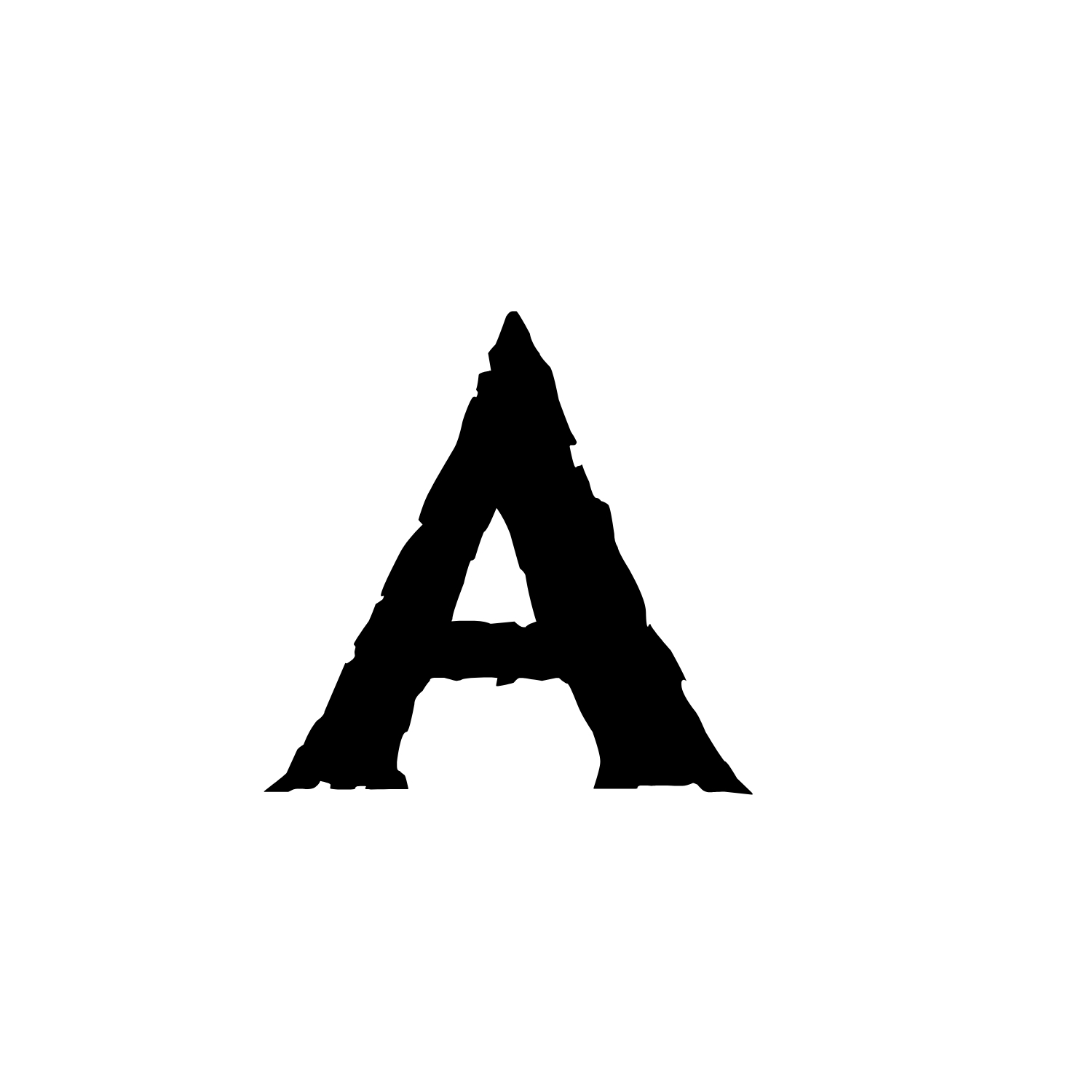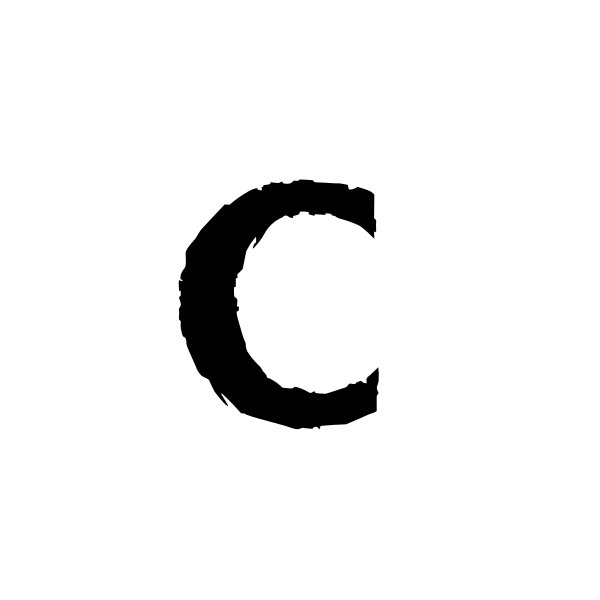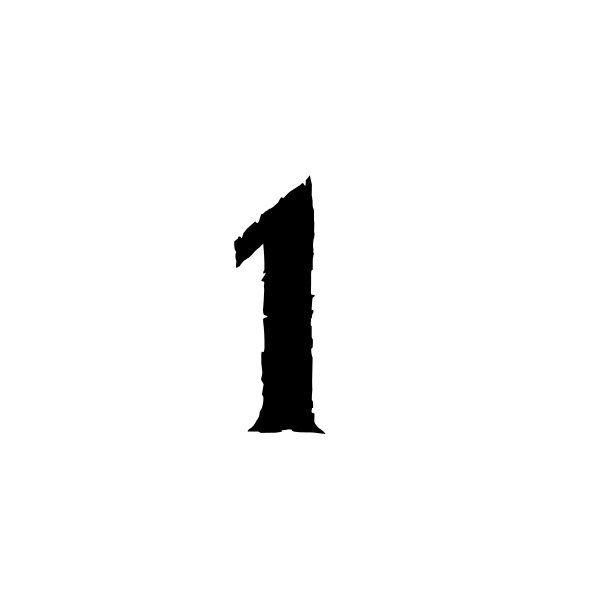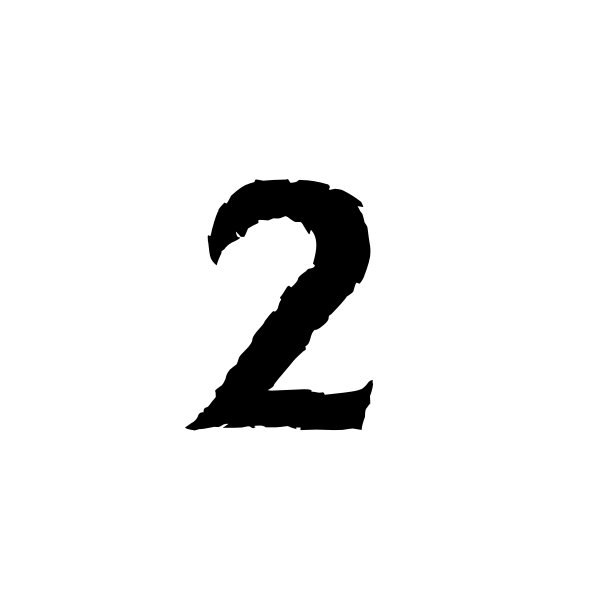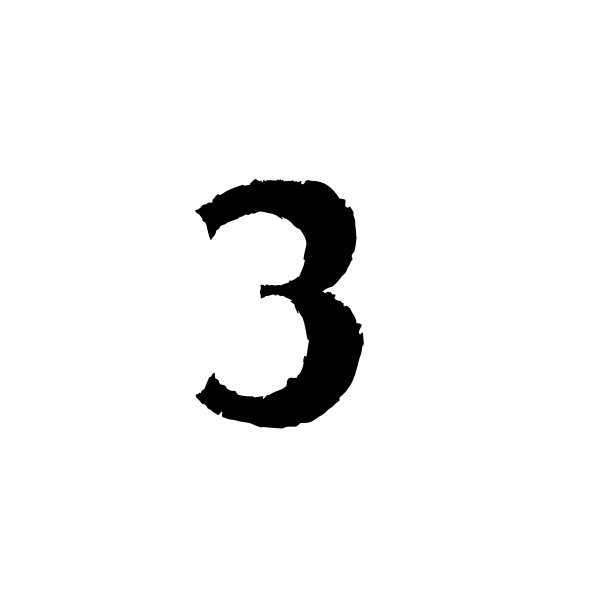
Frozen Font ist eine dekorative Schriftart im frostigen Stil – ideal für winterliche und verspielte Designs. Geeignet für Namen, Zahlen und individuelle Beschriftungen auf Textilien, Tassen, Karten oder Wanddekorationen.